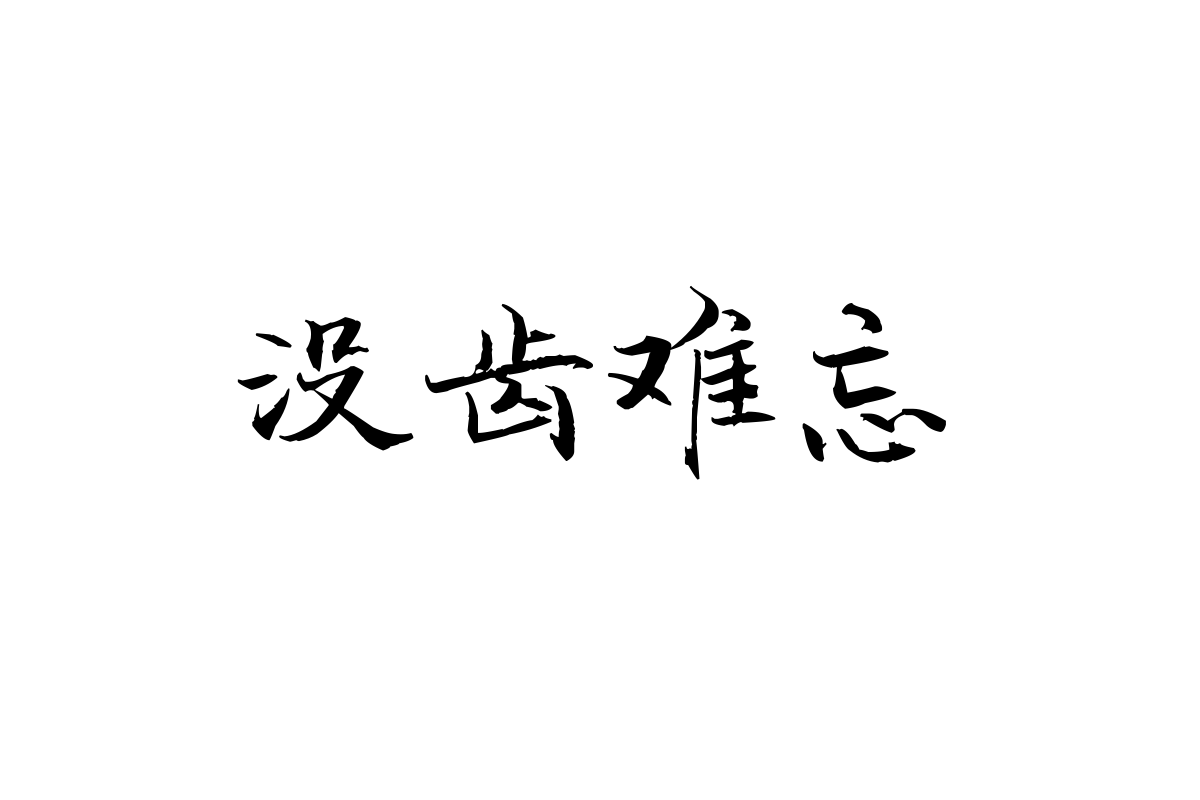
汉仪新蒂喜报行书体是一款具有中国传统风格的书法字体,它融合了现代设计理念和传统书法艺术的精髓。这款字体的特点是笔画流畅自然,字形优美大方,既有古典的韵味又不失现代感。
汉仪新蒂喜报行书体的笔画粗细适中,线条流畅有力,既适合用于正式的文件、报告等商务场合,也适合用于个人书写、签名等非正式场合。它的字形结构紧凑,布局均衡,给人一种庄重而大气的感觉。
此外,这款字体还具有一定的可读性,即使在快速阅读的情况下也能保证信息的清晰传达。同时,由于其独特的设计,使得它在视觉上具有很强的吸引力,能够给人留下深刻的印象。
总的来说,汉仪新蒂喜报行书体是一款非常适合用于各种场景的字体,无论是在商业还是个人使用中都能展现出其独特的魅力。